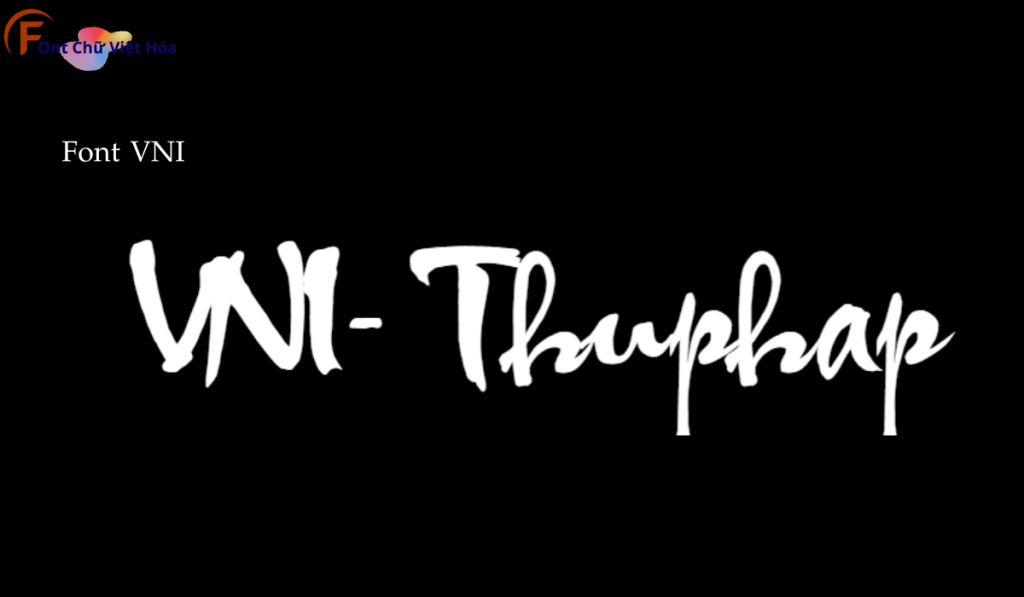
Font VNI Thu Phap Việt Hóa
Tác giả: VNI Thu Phap
Bộ Font: Font VNI
Phân loại: Cá tính, Độc đáo
Kiểu chữ: Thư pháp
Font VNI Thu Phap Việt Hóa, thuộc bộ font VNI, mang phong cách thư pháp mềm mại và tinh tế, phù hợp cho các dự án thiết kế như thiệp mời, bìa sách, và các sản phẩm thủ công. Với các nét chữ uyển chuyển và độ dày đều đặn, Font VNI Thu Phap Việt Hóa không chỉ dễ đọc mà còn tạo cảm giác nghệ thuật và thanh lịch. Việc Việt hóa font giúp người dùng dễ dàng tích hợp vào các thiết kế tiếng Việt, mang lại sự tiện lợi và nâng cao tính thẩm mỹ.